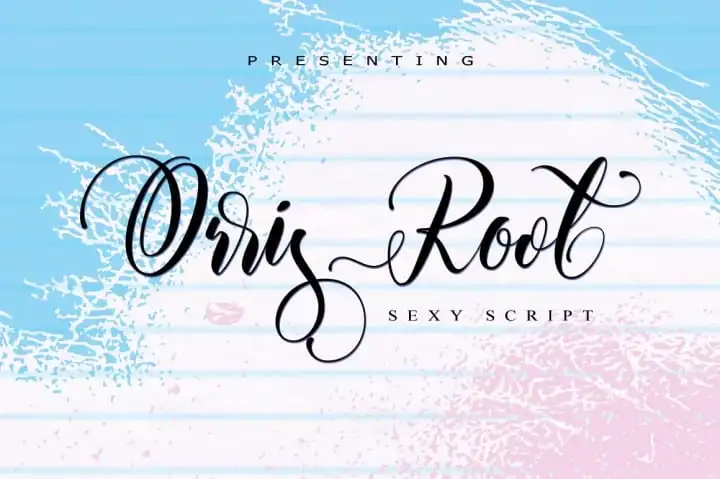
Orris Root Script Font – Download Grátis
Introduzimos a Fonte Script ‘Orris Root’, uma tipografia moderna criada à mão. Desenvolvida pelo designer individual 178-MC, esta é uma fonte premium que pode ser encontrada na Thehungryjpeg. A partir de hoje, está disponível de forma gratuita para download. Você estará muito bem-vindo a utilizar nossa oferta exclusiva em diversos projetos como convites de casamento, logotipos, assinaturas, designs de camisetas, cartas, impressões de citações, embalagens de produtos, cabeçalhos, blogs, grafitti e headlines para websites. Explore seu design incrível com esta fonte única.